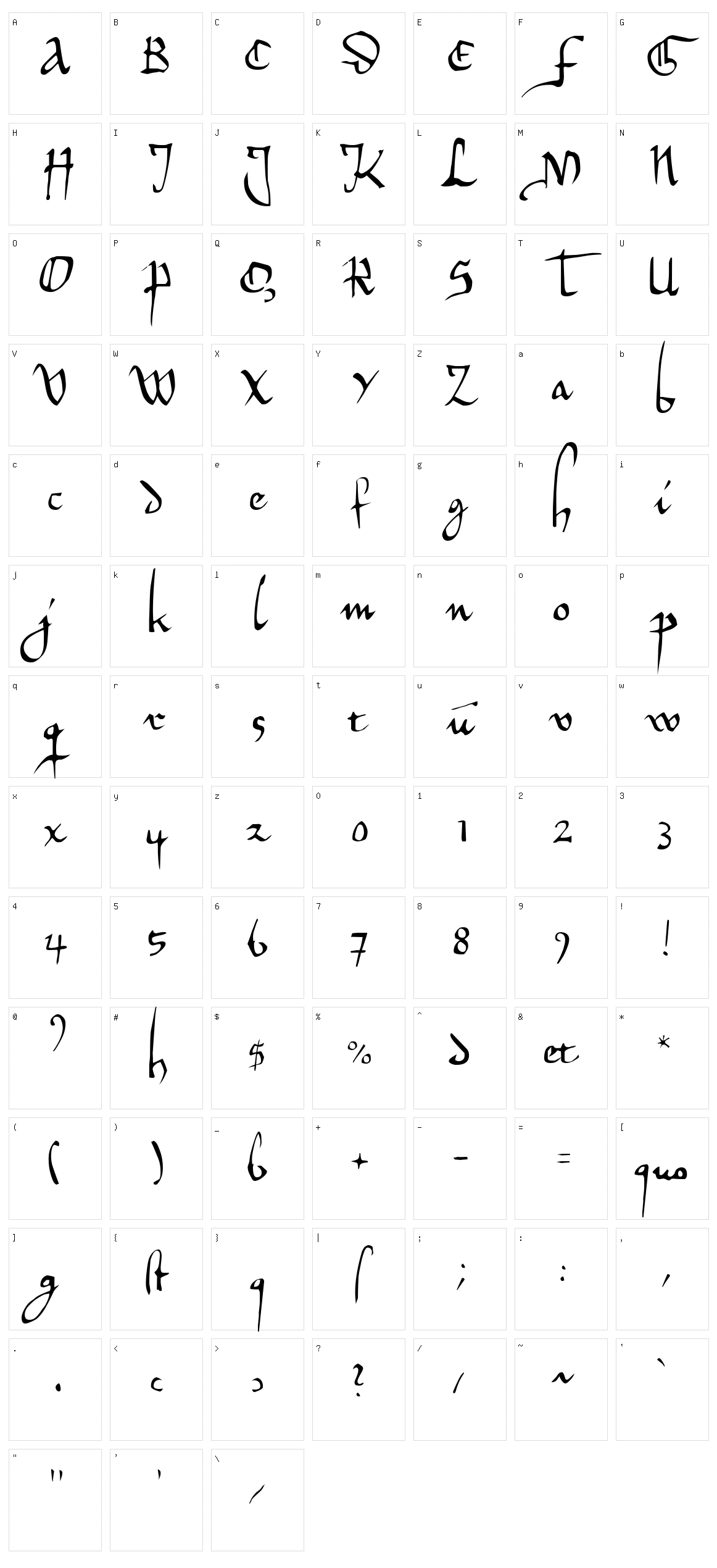
Herman Decanus: nach einer Urkunde aus dem 13. Jahrhundert, sogenannte Kanzleischrift, geschrieben von Dekan Hermann zu Soest, 1269. Diese Schrift zeichnet sich durch große Ober- und Unterlängen aus und eignet sich besonders für historisch wirkende Urkunden und Dokumente. Nichts für Leute mit Leseproblemen oder um viel Text auf einer Seite unterzubringen.
Die Schrift existiert in zwei Gewichten: normal und light.
Herman Decanus was inspired by a 13th century official document written by Dean Hermann of Soest, 1269. This font has extremely high ascenders and descenders, nothing to put much text on a page. Most of the uppercase letters are my invention, aimed to be readable for modern readers. Use it for documents that are meant to look "historical".
This typeface comes in two weights: regular and light.